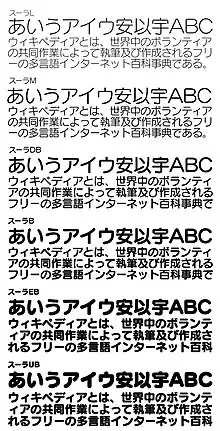
スーラ (書体)
背景
1990年前後の日本語DTP黎明期はデジタルフォントとしてリリースされていた書体が非常に限られており、とりわけ多種多様な書体が要求される広告制作・グラフィックデザインの現場においては完成度の高い丸ゴシック体の需要があった。特に大手プロダクションにおいては、旧版流用・修正再版といったニーズに対応すべく電算写植や専用組版システムで制作された在版をDTP化する作業が始まっていたが、写植全盛期にスタンダードな書体のひとつとなった写研のナールに替わるデザインのDTP用書体が存在せず、雰囲気の異なる書体によって代替せざるを得ない状況であった。
ほぼ同時期には同じく丸ゴシック体であるモリサワの「じゅん」ファミリーが電算写植用からDTP用フォントへと移植される形で発売されたが、本来、学参や設計図面用途を意識してデザインされた書体であったため、根本的にコンセプトが異なるものであった(※「じゅん」の名称の由来は「"Jun"ior」から)。
また、イワタの書体を字母とし、デジタルフォントに参入したピー・アンド・アイ社より、ナールを彷彿とさせる「カーサ」ファミリーが発売されたが、プリンタ専用フォントのみのリリースであったことなどから、あまり普及することはなくDTP導入直後の出版物などで使用されるにとどまった。
そうした状況において、スーラはナールとも共通するコンセプトを持つ書体であり、デザイン上の完成度はもとより、ファミリーの充実・ATM・外字への対応、後の組替え用仮名書体のリリースなどといった、フォント製品としてのサポート体制からもグラフィックデザイナーやエディトリアルデザイナーの間でも評価の高い書体のひとつとなった。高い視認性から、ナールと同様にグラフィックのみならず、プロダクトデザインなどでの使用例も多い。一例としては、かつてApple ComputerのMacintoshコンピュータ・iBookシリーズ・MacBook Proおよび同社キーボード単体製品において、キートップの刻印に採用された実績が挙げられる。
モリサワフォントをデファクトスタンダードとする現在の日本語DTP環境において、明朝体はリュウミン・ゴシック体は新ゴが標準的な書体として用いられるケースが多い中、丸ゴシック体においては同社のじゅん・新丸ゴではなく、スーラが同様の位置づけとして認識され、広告・雑誌などの商業印刷媒体から、屋外サイン、映像分野におけるテロップ・フリップまで幅広く使用されている(現在は新丸ゴも使用している)。
特にテレビ業界においてはHD化に伴うCG(キャラクタジェネレータ)・テロップ制作用機材の更新(写研のテロメイヤシリーズから他社テロッパーへの機材変更)に際し、機材への搭載フォントとして写研フォントが使用できなかったことから、その代替としてナールからスーラへと乗り換えたテレビ局やポストプロダクションも多く、在京局ではNHKやTBSテレビ(2007年4月 - )、テレビ朝日などが該当していたが、2015年時点では各局・番組を問わず、幅広く採用・導入されている。
ファミリー構成
- スーラL
- スーラM
- スーラDB
- スーラB
- スーラEB
- スーラUB